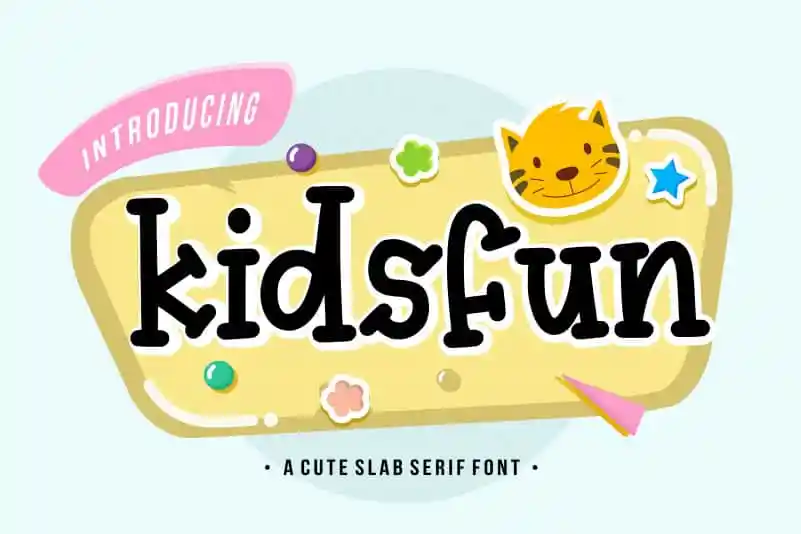
Kidsfun Slab Serif Font – Download Grátis
A Kidsfun Slab Serif é uma fonte ideal para vários aplicativos, desde o design de embalagens até a criação de anúncios e campanhas de marca. Seu grosso e robusto aspecto torna-a perfeita para usos que exigem destaque e impacto visual em ambientes como revistas, materiais de marketing e redes sociais. Além disso, ela se adapta bem a criações de eventos, como casamentos, expressando textos no topo da página ou sobre fundos coloridos de maneira elegante e moderna. Esta fonte é uma escolha conveniente tanto para designers profissionais quanto para iniciantes em busca de um recurso gráfico versátil que possa destacar sua mensagem em qualquer formato digital ou impresso.